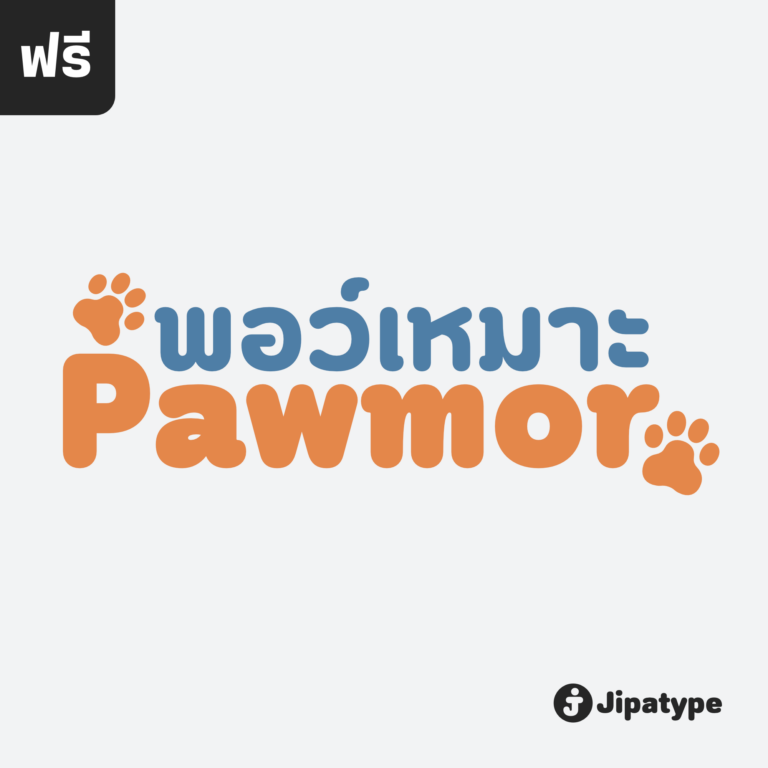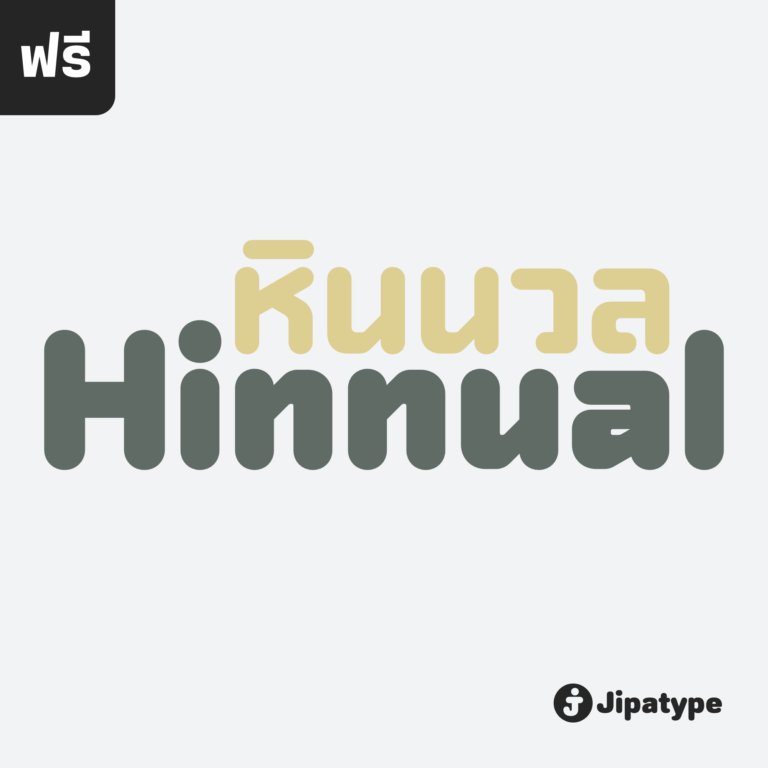
หวาน (SOV_Waan)
ฟอนต์หวาน ต้นทางจากป้ายร้านขนมหวาน ตัวแรกสูง ตัวกลางเล็กกว่า ตัวท้ายหางยาว
เป็นรูปแบบอักษรไม่มีหัว แนวแฟนตาซี คอมิดีการ์ตูน น่าร้าก…น่าชัง น้อนมีชื่อว่า “จ้ำม่ำ” มีทั้งแบบปกติ แบบตัวทับซ้อน พร้อมลวดลายกราฟิก โรยหน้าด้วยข้าวงอกบุบผกามาลาธัญพืช-ท็อปปิงเรนโบว์ แต่งสี 5 โทน 11 ชั้นเทมเพลต ฟรุ้งฟริ้ง-มุ้งมิ้งน่ากิ๊น…น่ากิน
ตัมตุ่ย แปลว่า “ตุ้มตุ้ย” น่ารัก ใช้เรียกเด็กผู้หญิงด้วยความเอ็นดู เป็นภาษาถิ่นใต้ นิยมใช้บริเวณอำเภอพะโต๊ะ และอำเภอหลังสวน รวมถึงอำเภอใกล้เคียง เอาคำนี้มาเป็นแรงบันดาลใจในการออกแบบฟอนต์ รูปแบบตัวหนังสือจะมีความหนาๆ อ้วนๆ น่ารักๆ
ส่วนผสมที่ลงตัวระหว่างความนุ่มนวลและความบึกบึน ฟอนต์พาดหัวตัวหนา ที่ร่างแบบด้วยการเขียนมือ บุคลิกเรียบง่าย แต่แสดงตัวตนได้อย่างชัดเจน
ฟอนต์อิกคิวซังเป็นฟอนต์แนวน่ารัก ตัวตลก ที่อ่านง่าย สวยงามน่ารัก ใช้ประกอบงานได้หลากหลาย แล้วแต่ช่างออกแบบจะนำไปต่อยอดออกแบบในงานได้ทั่วไป
ฟอนต์เจนจรัส แสงมน เป็นฟอนต์ตัวหนามนๆ อ่านง่าย ใช้ได้ทั้งฟิลลิ่งสนุก เรียบร้อย เหมาะกับเป็นหัวข้อหรือทำป้ายต่างๆ
Hinnual เป็นฟอนต์ที่ผสมผสานระหว่างรูปทรงสี่เหลี่ยมและทรงกลมเพื่อสร้างสไตล์ที่ไม่เหมือนใคร ชื่อมาจากคำไทย 2 คำ คือ Hin แปลว่า หิน และ Nual แปลว่า อ่อน ผสมผสานองค์ประกอบที่แข็งและอ่อนนี้สะท้อนให้เห็นในแบบอักษร ซึ่งมีเส้นที่สะอาดตาและเส้นคมซึ่งถูกทำให้อ่อนลงด้วยมุมโค้งมน ฟอนต์มีให้เลือกถึง 18 แบบ มีตัวเลือกหลากหลายให้คุณได้เลือกใช้ Hinnual เหมาะอย่างยิ่งสำหรับใช้ในพาดหัวและพาดหัวย่อย ซึ่งลักษณะที่โดดเด่นสามารถช่วยดึงดูดความสนใจของผู้อ่านได้ เส้นสายที่สะอาดตาและสไตล์ที่เป็นเอกลักษณ์ยังทำให้เป็นตัวเลือกที่ยอดเยี่ยมสำหรับแบรนด์ โลโก้ และงานออกแบบอื่นๆ ที่ต้องการภาพลักษณ์ที่น่าจดจำ โดยรวมแล้ว Hinnual เป็นฟอนต์อเนกประสงค์และสะดุดตาที่ผสมผสานองค์ประกอบทั้งความแข็งแกร่งและความนุ่มนวล การออกแบบที่เป็นเอกลักษณ์ทำให้เป็นตัวเลือกที่ยอดเยี่ยมสำหรับนักออกแบบที่ต้องการสร้างผลงานที่น่าจดจำ ออกแบบโดย : อานุภาพ ใจชำนาญ (Anupap Jaichumnan)สามารถทดลองใช้เวอร์ชันฟรีผ่านแอปฯ ของจิปาไทป์ได้ในเชิงพาณิชย์ ดูรายละเอียดและดาวน์โหลดแอปฯได้ที่ : jipatype.com
ขอแนะนำ Pawmor ฟอนต์ sans-serif ใหม่ที่น่ารักและขี้เล่น ซึ่งจะเพิ่มความน่ารักให้กับงานออกแบบของคุณ! แบบอักษรนี้เหมาะสำหรับโปรเจกต์ที่เกี่ยวข้องกับสัตว์เลี้ยงหรือสัตว์ต่างๆ ด้วยขอบที่โค้งมนและส่วนโค้งที่นุ่มนวล ให้ความรู้สึกอบอุ่นและเป็นกันเองจนยากจะต้านทาน Pawmor มีให้เลือกถึง 18 แบบ ให้คุณได้เลือกใช้ตามความต้องการของคุณ ด้วย Pawmor คุณสามารถสร้างงานออกแบบที่สะดุดตาสำหรับธุรกิจเกี่ยวกับสัตว์เลี้ยง งานกิจกรรมต่างๆ เกี่ยวกับสัตว์ โดยรวมแล้ว Pawmor เป็นตัวเลือกที่สมบูรณ์แบบสำหรับทุกคนที่ต้องการเพิ่มความแปลกใหม่และความสนุกสนานให้กับงานออกแบบของคุณ ออกแบบโดย : อานุภาพ ใจชำนาญ (Anupap Jaichumnan)สามารถทดลองใช้เวอร์ชันฟรีผ่านแอปฯ ของจิปาไทป์ได้ในเชิงพาณิชย์ ดูรายละเอียดและดาวน์โหลดแอปฯได้ที่ : jipatype.com
โดยปกติแล้วเป็นชอบกินน้ำผลไม้ปั่นมากๆ และได้เห็นป้ายขายในรูปแบบต่างๆ ซึ่งมันทำให้ผมเกิดไอเดียในการอยากจะเขียนฟอนต์นี้ขึ้นมา เพื่อให้ทุกๆ คนได้ฟอนต์แนวน่ารักๆ กวนๆ ตามสไตล์ของตัวผมเอง ก็เลยออกแบบฟอนต์นี้มาครับ